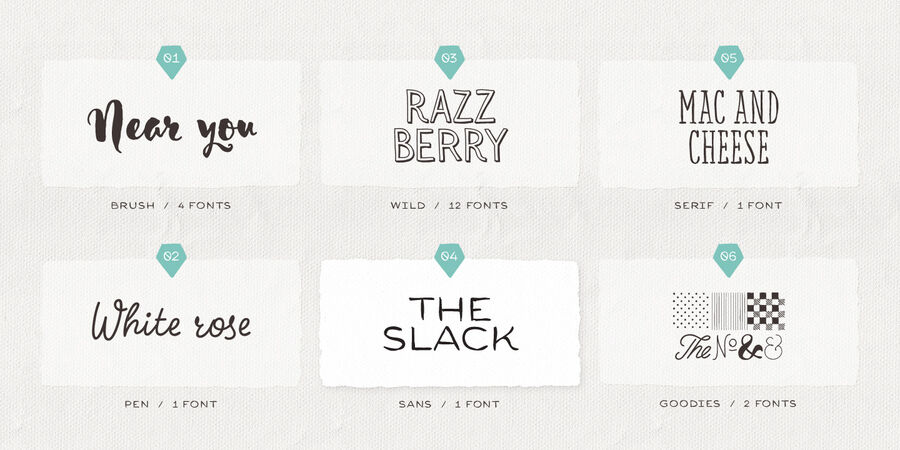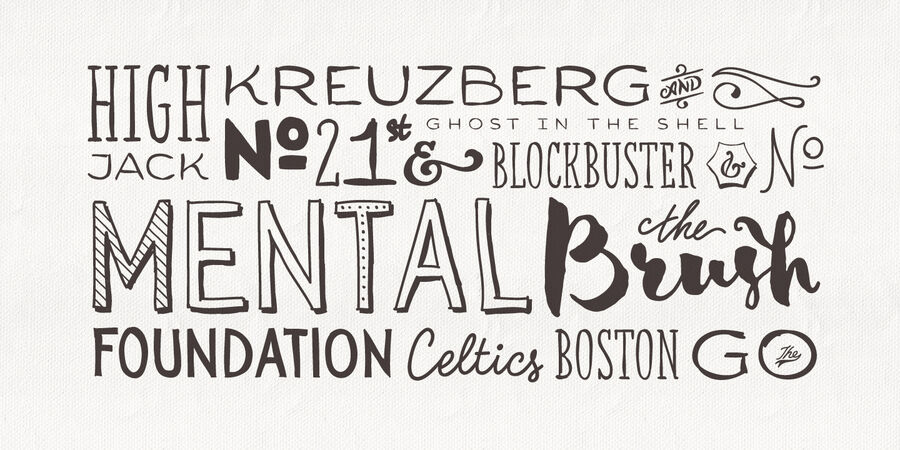
Шрифт Sensa – це сімейство шрифтів ручної роботи, що складається з 21 накреслення. Серед інших рукописних шрифтів цей поділяється на 6 підродин, кожна з яких вносить свій внесок у широкий діапазон настроїв – Sensa Brush, Sensa Pen, Sensa Wild, Sensa Sans, Sensa Serif та Sensa Goodies. Виберіть будь-який із шрифтів Sensa в якості провідного, а решта шрифтів можуть з легкістю супроводжувати його. Щоб працювати разом у всіх можливих комбінаціях, всі шрифти в цьому наборі створені з урахуванням цієї простої ідеї. Шрифт Sensa можна застосувати практично для будь-якого дизайнерського проекту – від реклами, упаковки, редакторських і брендингових робіт до веб, соцмереж та екранних проектів. Для краси та ніжних відчуттів або для більш чоловічого та сильного спілкування – у вас є широкий вибір. Гарнітура підтримує кирилицю. 2 шрифти Sensa доступні БЕЗКОШТОВНО. Функції OpenType: стилістичні альтернативи, контекстуальні альтернативи, розчерки, локалізовані форми. Шрифт розроблений командою Fontfabric в 2015-2018 роках.
Асоціації з сімейством шрифтів Sensa SansОсобистість і характер гарнітури: